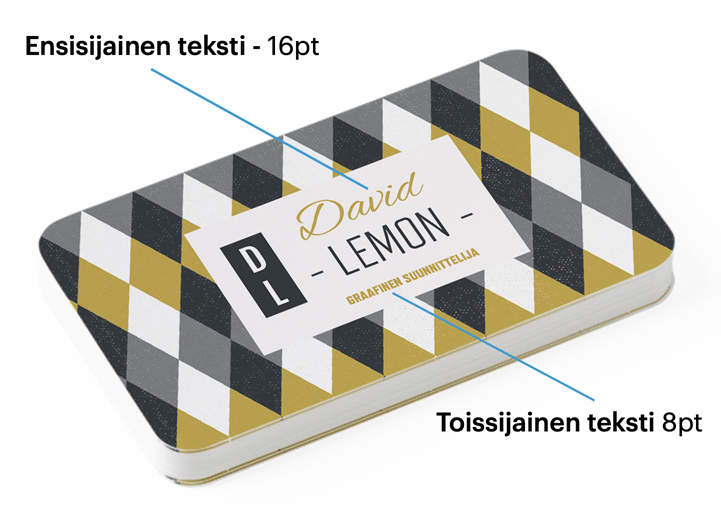
Kuvittele, että: Avaat käyntikortin mallipohjan ja kirjoitat siihen yrityksesi nimen. Se näyttää pikkuriikkiseltä valkoista taustaa vasten, joten suurennat fonttikokoa. Selaat fonttivalikkoa ja kokeilet, miltä erilaiset kirjasintyylit näyttävät. Selaat (näennäisesti) loputonta kirjasinluetteloa, ja ennen kuin huomaatkaan, tunnet olosi entistä epävarmemmaksi.
Yrityksesi määrittävän typografisen tyylin valitseminen tuhansien fonttien joukosta on haastavaa. Käyntikortissa käyttämälläsi kirjasintyylillä on kaksi päätehtävää – kiinnittää huomio ja olla helppolukuinen.
Seuraavassa perehdytään typografian merkitykseen suunnittelussa ja paljastetaan parhaiten käyntikortteihin sopivat fontit. Lue lisää eri kirjasintyypeistä, kuinka yhdistellä erilaisia tyylejä ja minkä kokoinen käyntikortin tekstin olisi hyvä olla.
Fontti syntyy yhdistelemällä kirjaintyylejä, numeroita, aksentteja ja symboleja.
23 PARASTA FONTTIA KÄYNTIKORTTEIHIN
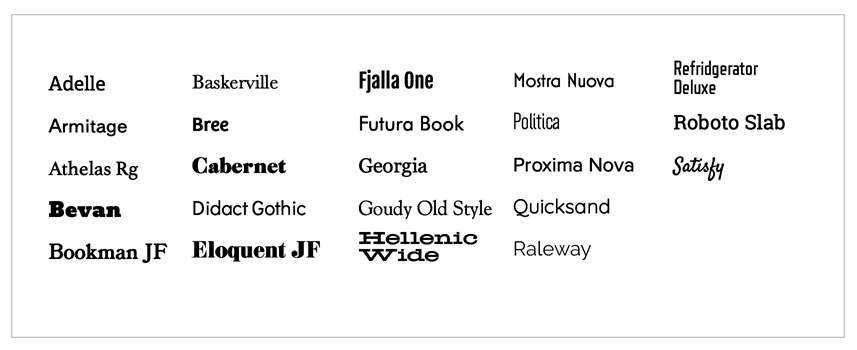
Adelle • Armitage • Athelas Rg • Bevan • Bookman JF • Baskerville • Bree • Cabernet • Didact Gothic • Eloquent JF • Fjalla One • Futura Book • Georgia • Goudy Old Style • Hellenic Wide • Mostra Nuova • Politica • Proxima Nova • Quicksand • Raleway • Refrigerator Deluxe • Roboto Slab • Satisfy
Fonttityylit: serif & sans-serif
Mitä sans-serif tarkoittaa?
Typografiassa sans-serif tarkoittaa fonttia ilman koristeellisia pääteviivoja (serif). Sans-serif-kirjasintyylissä on yleensä vähemmän viivan leveyden vaihteluita kuin serif-kirjasintyylissä (tästä tarkemmin myöhemmin). Painotuotteissa sans-serif sopii parhaiten käytettäväksi yritysnimiin ja otsikoihin, koska se on helppo lukea yhdellä silmäyksellä. Sans-serif on yleensä paras moderni fontti käyntikorttiin, koska se on yksinkertainen ja minimalistinen.
Sans-serif-fontteja käytetään myös digitaalisena näyttötekstinä. Pienemmällä tarkkuudella varustetulla näytöllä fontin hienot yksityiskohdat katoavat helposti tai ne saattavat näyttää liian suurilta. Kannattaa siis pitää sans-serif-fontit mielessä, kun työstät näkyvyyttäsi niin verkossa kuin sen ulkopuolella.
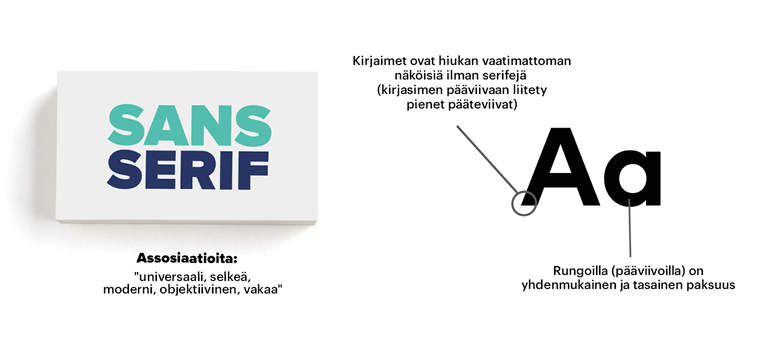
Jos mietit mistä termi “sans-serif” tulee: “sans” on ranskaa ja tarkoittaa “ilman”, kun taas “serif” saattaa olla hollantilaista alkuperää – “schreef” tarkoittaa “viiva”.
Mitä serif tarkoittaa?
Sana serif on peräisin historiallisiin rakennuksiin, siltoihin ja hautakiviin kaiverretuista merkinnöistä. Sanan viittaus historiaan on ihanteellinen, kun haluat antaa tuotemerkillesi perinteisen tai vakiintuneen ilmeen.
Perinteikkyyden ja luettavuuden vuoksi serif-fontteja käytetään yleensä pitkissä käsikirjoituksissa, kirjoissa, sanomalehdissä ja aikakauslehdissä. Jotkut uskovat, että serif-fontti parantaa pitkän tekstin luettavuutta, koska pääteviivat auttavat silmiä pysymään rivillä. Toiset taas uskovat, että serif-fontit toimivat pitkässä tekstissä, koska olemme tottuneet siihen.
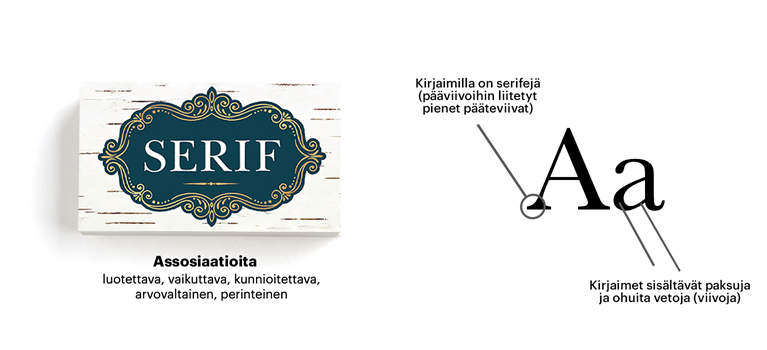
Jos haluat käyntikorttisi serif-fontin kiiltävällä kohokuvioinnilla, lisää tehoste vain suurimpaan tekstikenttään – kuten vaikkapa yrityksesi nimeen.
Miten hyödyntää kaunotyyliä
Kaunotyyliset fontit ovat kirjasimia, jotka muistuttavat käsinkirjoitettua tekstiä esimerkiksi kursiiviviivojen ja käsinkirjoitetun tyylin kalligrafian avulla. Kaunokirjoitusfontit sopivat erinomaisesti kutsuihin, onnittelukortteihin, otsikoihin tai kertaluonteisiin henkilökohtaisiin viesteihin. Klassinen, kursiivi kaunokirjoitus saa yleensä aikaan tyylikkään ilmeen, kun taas pyöreämpi fonttityyli luo kepeän vaikutelman.
Käsialamainen kirjasintyyppi on hyvä valinta kiinnittämään lukijan huomion, mutta kannattaa varmistaa, että viesti on edelleen helppolukuinen. Älä käytä kaunotyylistä fonttia pitkiin tekstipätkiin, koska sitä on vaikea lukea pienikokoisena. Jos kuitenkin haluat käyttää käyntikortissasi kaunofonttia, käytä sitä toisen tason tekstiin, kuten iskulauseeseen tai mottoon.
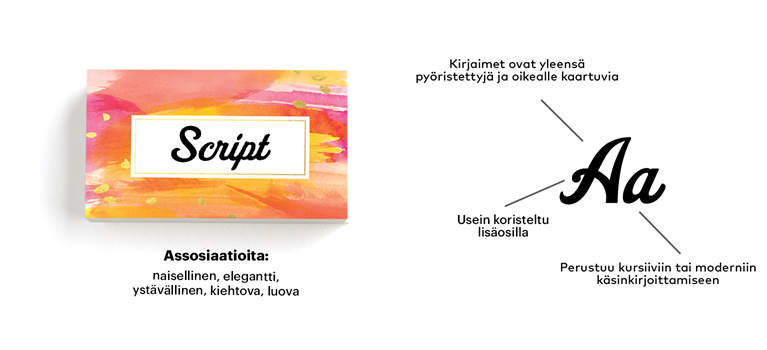
Kuinka yhdistellä fontteja käyntikortissa
Kun suunnittelet käyntikorttiasi, rajaa käyttämiesi fonttien määrä kahteen. Suunnittele visuaalinen hierarkia ja päätä, minkä tiedon tulisi olla kaikista näkyvin – luultavasti oma nimesi tai yrityksesi nimi. Muut tiedot, kuten yhteystiedot ja someviitteet, voivat olla pienemmät ja eri fontilla.
Seuraavassa lisää vinkkejä fonttien käyttöön käyntikortissa:
- Yhdistä kaunotyylinen tai serif-fontti sans-serif-fonttiin.
- Älä käytä toisiaan muistuttavia fonttityylejä.
- Käytä saman fontin eri korostuksia (lihavoitu, tavallinen, kursiivi) luomaan kontrastia.
- Älä käytä yli kolmea fonttikokoa. (Kaksi kokoa toimii yleensä parhaiten!)
- Huolehdi tekstin ja taustan välisestä kontrastista… Tekstin pitää selkeästi erottua.
Neljä fonttiyhdistelmää inspiroimaan seuraavaa käyntikorttiasi
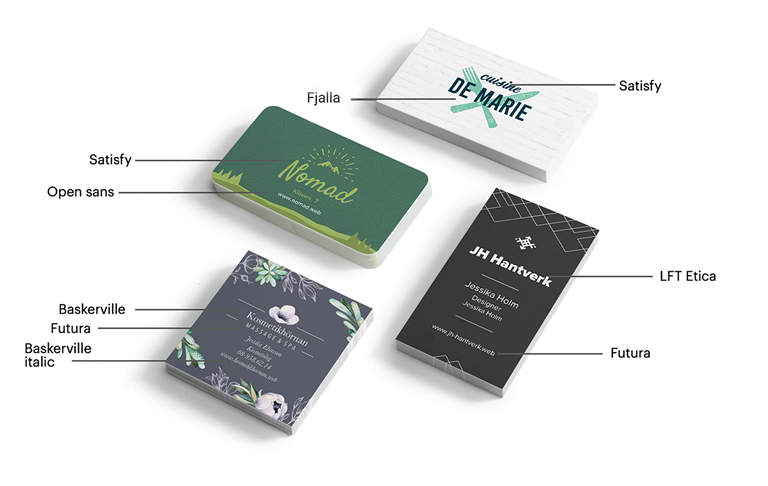
Kirjasinkoot käyntikortissa: Parhaaksi havaitut yhdistelmät
Typografiassa pistekoko (pt) on standardi mittayksikkö mitattaessa kirjainkokoa. Näkyvien käyntikorttitekstikenttien, kuten yrityksen tai henkilön nimen, tulisi olla välillä 10–16 pt, riippuen siitä, kuinka paljon tilaa on käytettävissä.
Ole varovainen käyttäessäsi kauno- ja serif-fontteja pienikokoisina. Jos sinun on sisällytettävä korttiin pientä tekstiä, käytä sans-serif-fonttia luettavuuden parantamiseksi.